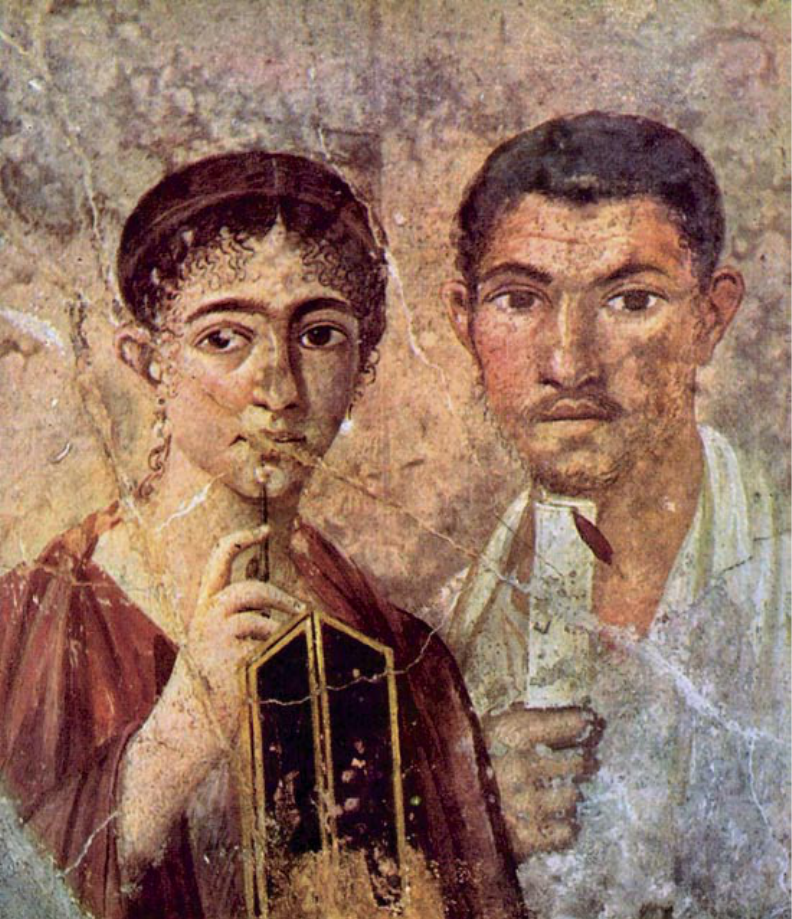
Cadernos de Tipografia 5
Como é que os Romanos escreviam?
mas também contributos de estudantes e até princi-
piantes, que trouxeram abordagens frescas. É um ver-
dadeiro prazer fechar este ano com tão excelentes arti-
gos como o de Olcar Alcaide, na página 17 – um mini-
romance histórico, uma maneira encantadora e ver-
dadeiramente original de abordar um tema essencial,
mas já muito cansado de ser académico: a origem das
nossas letras no Império Romano.
Os temas deste Nr 5, o último Caderno de 2007, con-
centram-se em três grandes blocos: Novidades, as le-
tras da Era romana, e o uso das Capitulares.
Boa Leitura!
III. Congreso de Tipografía .............................2
Tipos Latinos 2008 ..........................................4
Papel digital, 2007 ..........................................5
iPaper em Portugal ......................................... 7
O magnífico trabalho da OTSP ......................8
Maestría en Diseño Tipográfico
Mestrado em typeface design no México ............11
VTOPIENSIVM ALPHABETVM .................13
A letra global .................................................. 16
La Capitalis Monumentalis
y el rugido del León .................................. 17
A Cursiva romana .......................................... 25
«Romanas» sem serifas .................................29
A Capitalis Rustica ........................................30
As pixelizações de letras romanas ................34
Letras romanas de metal ...............................36
A Taquigrafia romana ................................... 37
Inscrições em argila ....................................... 41
Romanas digitalizadas .................................. 43
Organizando o texto:
Capitulares e Iniciais ................................48
Capitulares unciais ........................................ 59
Tipografía en la era
de la globalización
¿Qué aspectos positivos ha tenido la globalización para la tipografía? ¿Y cuáles han
sido los negativos? ¿Se puede ser local y global al mismo tiempo? Realmente, ¿po-
por contignatio, ou pelo uso de abreviaturas ou siglas.
O mais belo exemplo de cursiva romana em
território português: Inscrição em barro fresco,
oficina de um oleiro de Conímbriga.
Fragmento da lei
municipal ampuritana de época
augustal, escrita com cursivas
sobre placa de bronze.
Uma jovem
senhora, mostrada
com a caneta (stylus) usada
para escrever sobre tabuínhas
de cera. Penteado à moda da
época de Nero. Museu de
Arqueologia de Nápoles.